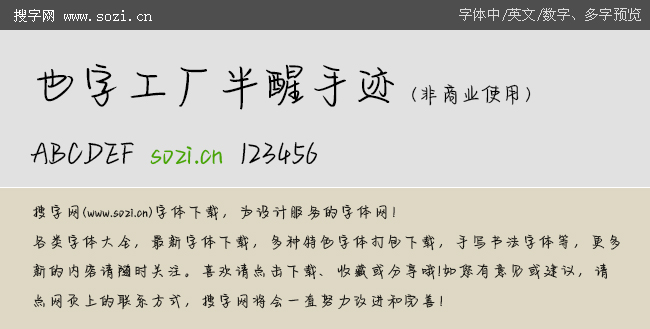
也字工廠半醒手跡
搜字網(wǎng)給大家提供一款也字工廠半醒手跡(非商業(yè)使用)中文字體下載,也字工廠半醒手跡是一款手寫風(fēng)格的書法字體,字體為硬筆書法字體,書寫流暢自然,具有很好的視覺效果。適合應(yīng)用于藝術(shù)設(shè)計(jì)、平面宣傳設(shè)計(jì)、網(wǎng)頁設(shè)計(jì)、海報(bào)設(shè)計(jì)等應(yīng)用(此字體為個(gè)人非商用版,商用可以聯(lián)系:官方網(wǎng)址:https://yefont.com/home,聯(lián)系方式:13798980448)。